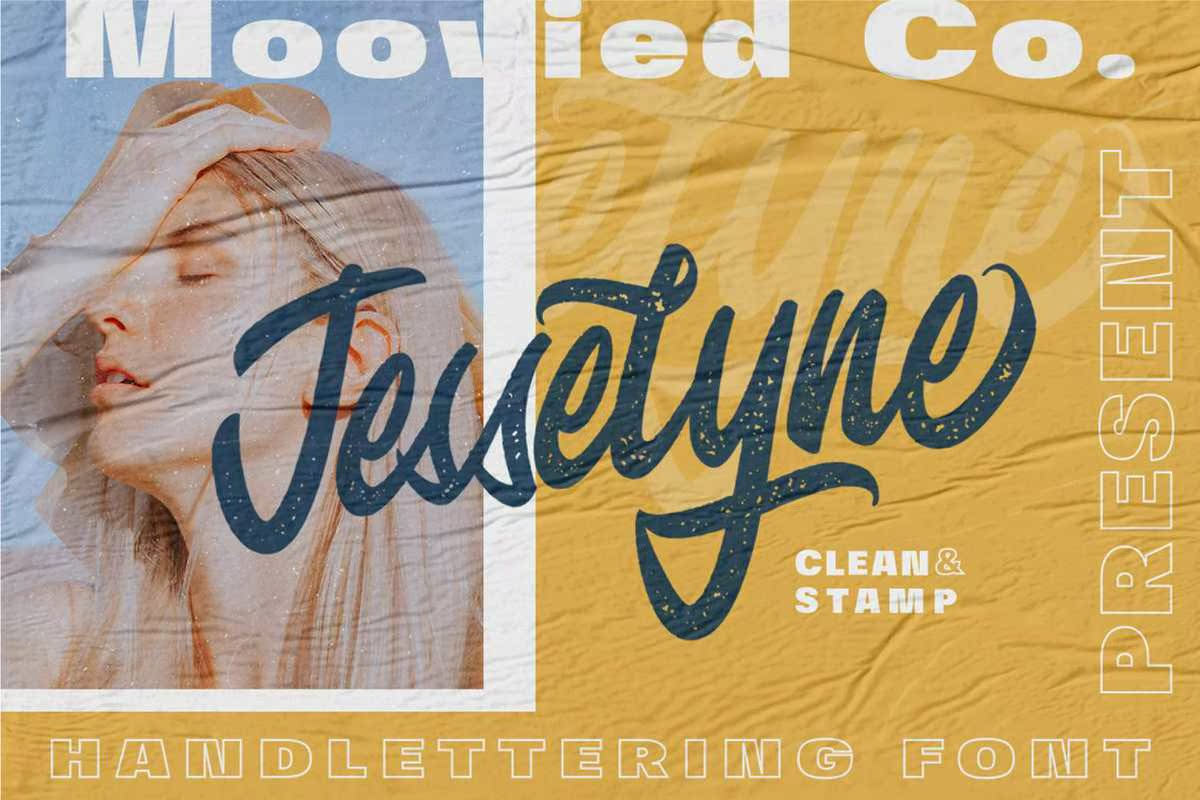
JesselyNes由Urban、Streetwear和VintageMadeWith Handletting Style.创意品牌、徽标、手写报价、产品包装、标题、海报、商品、社交媒体/秘密、特殊元素等创作。JesselyNes由Urban、Streetwear和VintageMadeWith Handletting Style.创意品牌、徽标、手写报价、,产品包装、标题、海报、商品、社交媒体/秘密、特殊物品等。